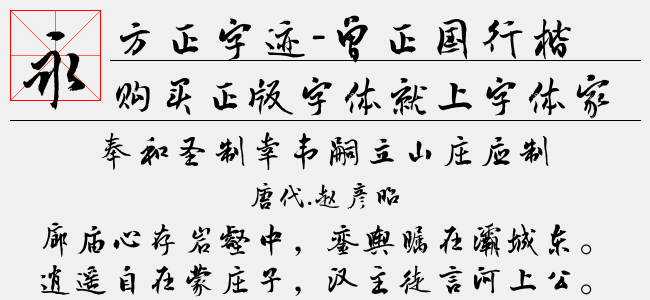
方正字迹-曾正国行楷简体
字体名称:方正字迹-曾正国行楷简体
字体字数:26个英文大小写字母及和阿拉伯数字
书体类型:创意图形类
方正字迹-曾正国行楷简体
方正字迹-曾正国行楷简体是一款接地气有个性的手写中文简体,她比较适合用于相关的广告设计,PS软件内嵌以及海报设计应用等,字体家网站是一家专业发布字体下载和免费字体下载和正版授权的字体网站,有叶根友字体以及汉仪字体,方正字体等。